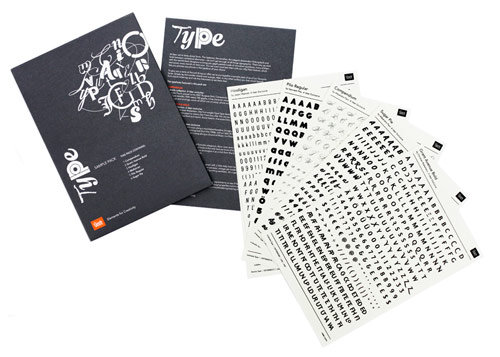
Veer bietet zahlreiche neue Schriftarten an, u.a. die neuesten von Alejandro Paul, Jason Walcott, Rian Hughes und Stefan Hattenbach. Wer sich bei Veer als Kunde anmeldet, hat die Möglichkeit, ein kostenloses Type Transfer Set zu ergattern, das sechs Schriftproben aus der Veer Online Kollektion beinhaltet.
Alejandro Paul ist einer der gefragtesten Schriftdesigner bei Veer. Für seine früheren Arbeiten hat er bereits zahlreiche Auszeichnungen erhalten, z.B. durch die Bienal Tipos Latinos in Lateinamerika und den Type Directors Club in Nordamerika. Seine neue Schriftart, Business Penmanship, ist eine Ode an vergangene Zeiten, in denen die Schreibkunst im Geschäftsalltag noch eine große Rolle spielte. Sie umfasst über 1200 Zeichen, einschließlich Ligaturen, stilistischer Alternativen und einer Reihe von Zierbuchstaben und Ornamenten. Die Schriftart enthält auch Zeichen aus diversen romanischen Sprachen West- und Mitteleuropas sowie des Baltikums.
Zusätzlich zu Business Permanship stellt Veer weitere exklusive Schriftarten vor:
Martian Text, von Jason Walcott entworfen, ist eine stark stilisierte geometrische Schriftart mit dem Kreis als Grundelement. Sie trägt Merkmale des Futurismus und des Art-Déco-Stils.
Paralucent Text von Rian Hughes, eine neue Version der ursprünglichen Paralucent, wurde der steigenden Nachfrage nach dieser Schriftart für kleine Textgrößen angepasst. Sie hat nun eine größere Laufweite, mehr offene Punzen und einen größeren Abstand zwischen Strich und Bogen. Die Schriftart ist in einem einfachen und praktischen Viererpaket erhältlich: „Buch“, „Buch kursiv“, „Fett“ und „Kursiv fett“. Im OpenType-Format werden alle mitteleuropäischen Sprachen unterstützt.
Mit Replay erweckt Stefan Hattenbach eine klassische Schriftart aus dem 18. Jahrhundert von William Caslon zu neuem Leben. Sie ist dreimal im normalen, dreimal im kursiven und einmal im Display-Schnitt verfügbar, jeweils mit Kleinbuchstaben, diversen Zahlen, Zierbuchstaben, zusätzlichen Ligaturen und einer Vielzahl stilvoller Ornamente.
Zur Einführung der neuen exklusiven Schriftarten bietet Veer Kunden bei der Anmeldung ein kostenloses Type Transfer Set, das sechs Schriften aus Veers Online-Kollektion beinhaltet. Diese Schriftproben können auf einer Vielzahl von Oberflächen genutzt werden. Kunden können so die Schriften von Veer genau prüfen und gleichzeitig spielerisch die gesamte Schriftpalette ausprobieren.
„Schriftarten sind weiterhin im Trend. Sie werden immer kunstvoller und treiben die Weiterentwicklung der Schrifttechnologie ununterbrochen voran“, so Joe Newton, Produktmanager für Schriften bei Veer. „Alejandros Business Penmanship ist ein hervorragendes Beispiel dafür, wie diese Schriftarten aufgrund von Kontext und Nähe zu anderen Buchstaben automatisch andere Bildzeichen ersetzen. Wir haben viele neue Schriften in unsere Kollektion aufgenommen, die Ausdruck anderer bekannter Trends sind, z.B. geometrische, serifenlose Schriften, Schriften im Viktorianischen Stil, im Stil des Holztafeldrucks etc.“
Abgesehen von den neuesten exklusiven Schriften hat Veer viele andere Schriftarten eingeführt, u.a. Adios,Semilla,Theorem und Biographer von Alejandro Paul, Beauchef von Juan Pablo De Gregorio, De Soto von Stephen Rapp, Moped und Phaeton von Randy Jones, zahlreiche neue Schriftarten der bedeutenden französischen Foundry Porchez Typofonderie sowie 40 neue Schriftarten von TypeTrust.
Die Kollektion von Veer knüpft an andere bekannte Kollektionen wie Umbrella™ an, die Arbeiten wie Compendium von Alejandro Paul, Grant Avenue von Christian Robertson und Cordial Bloom von Riccardo Olocco und Daniele Zanoni beinhaltet.
Auf der Community-Webseite „Veer Ideas“ wurde ein neuer Bereich „Kerned Events“ eingerichtet. Dort geht es ausgehend von den neuen Schriften um den Umgang mit Schrift in verschiedenen Bereichen. Kerned Events wird täglich von Veer und einer wachsenden Anzahl von Grafikdesignern weltweit aktualisiert und zeigt, wie Schrift auf spielerische und kreative Weise eingesetzt werden kann.